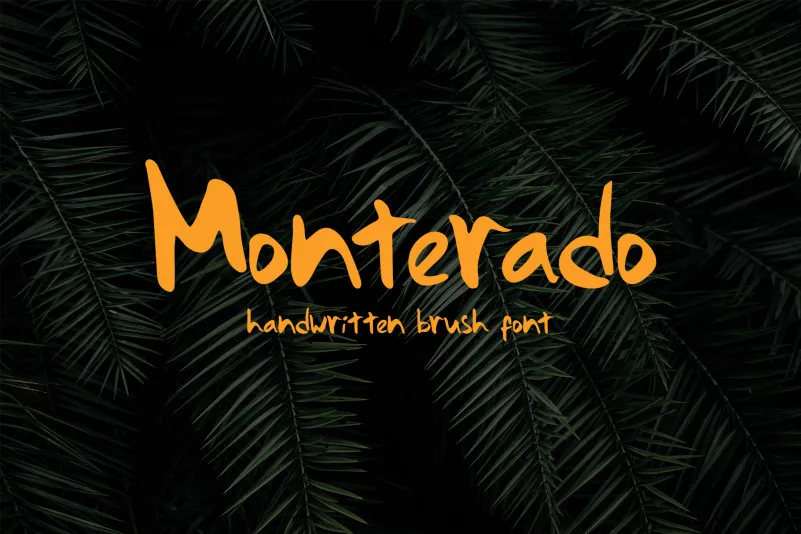
Monterado – Handwritten Brush Font – Download Grátis
A Monterado Font é uma experiência visual realista que remete diretamente à arte do autographado. Ela surge das raspuras dos papéis escritos a mão, preservando um encanto natural e autêntico. Esta fonte brush tem seu próprio jeito único de se expressar, não apenas como texto, mas também como uma testemunha ativa da vida que passou por ela. Quer seja para um projeto editorial, publicação online ou até mesmo uma obra de arte digital, a Monterado oferece a sensação do papel real e dos dedos desenhar. Suas letras são suaves e vivas, transmitindo um estilo único que traz consigo uma autenticidade natural. Esta fonte é mais do que apenas letra; ela é parte integrante da história das mãos que a criaram. Designada pela Wellscriptstudio, essa font apresenta uma riqueza de detalhes que complementam suas características distintas, tornando-a perfeita para quem busca algo autêntico e natural em seus projetos digitais.